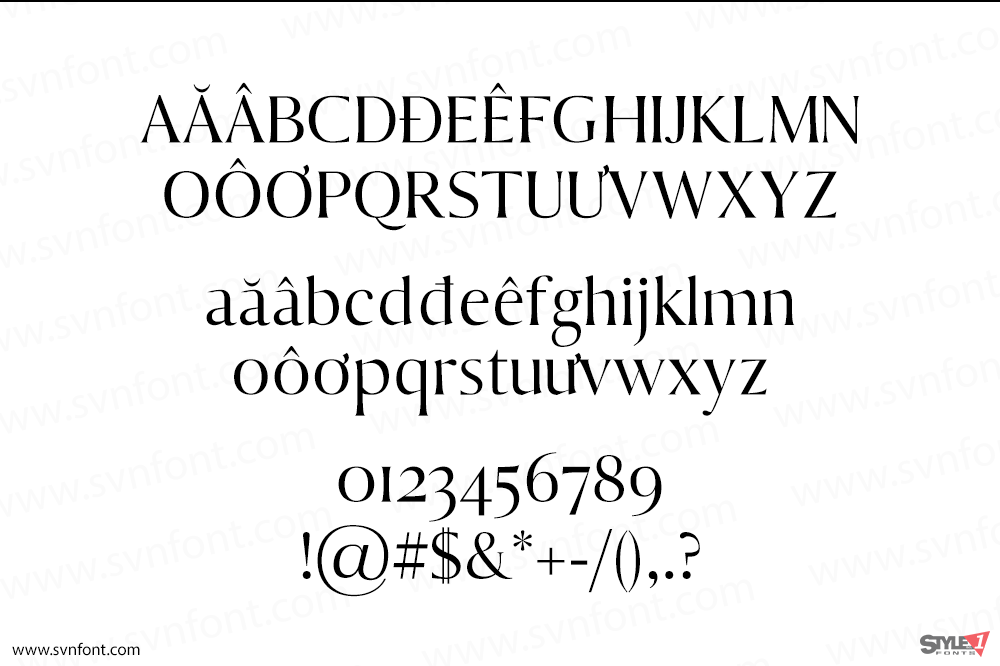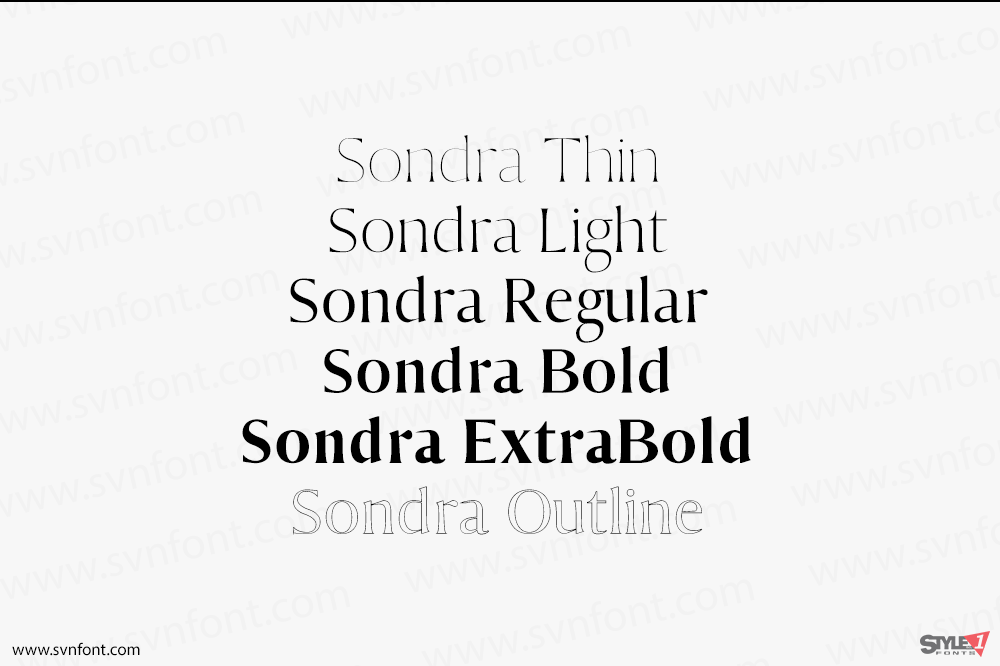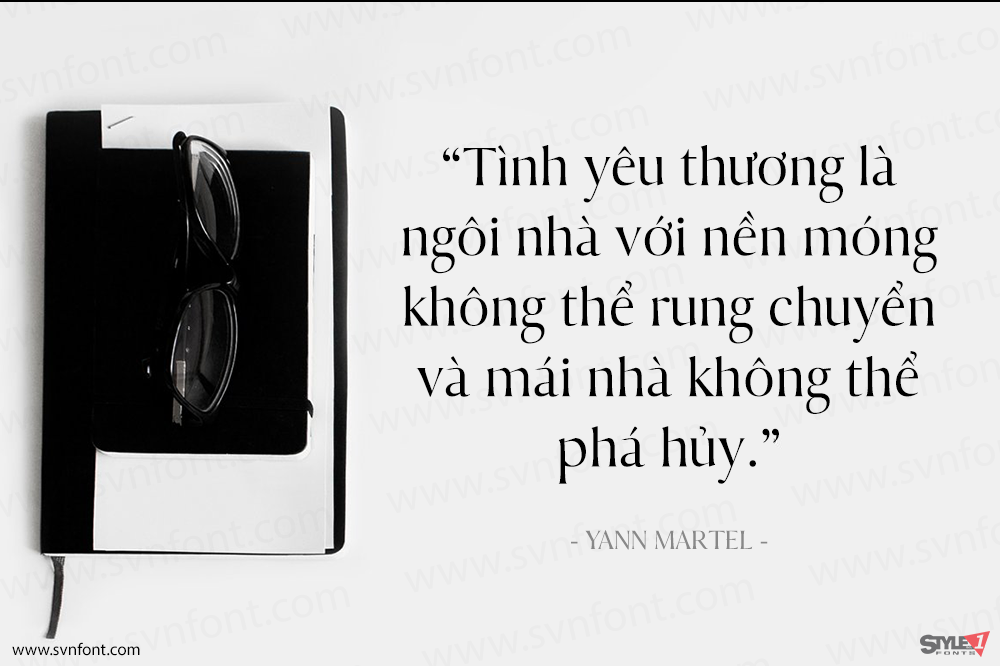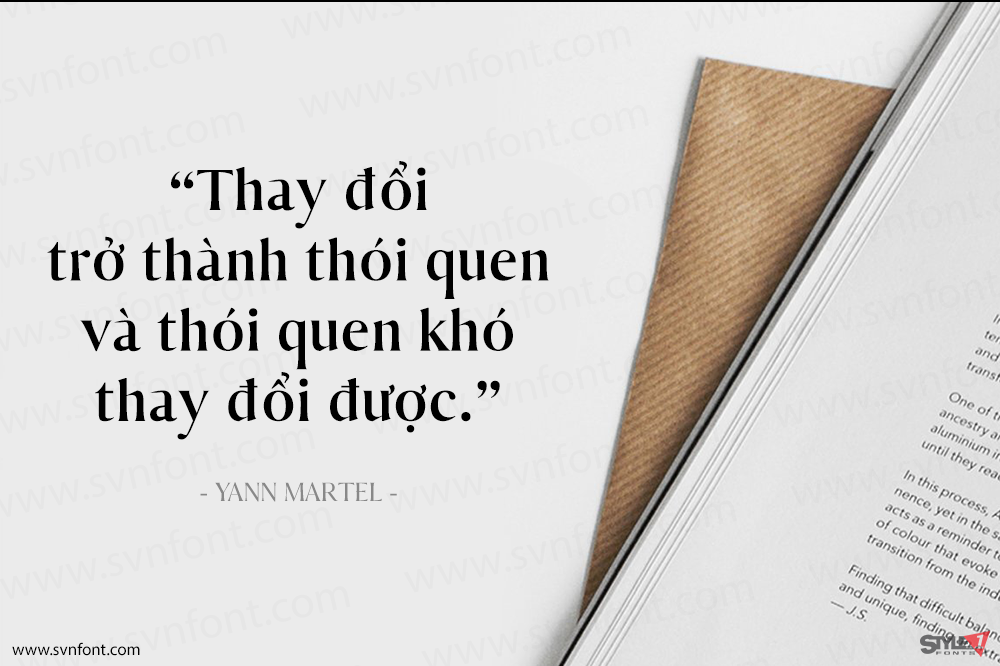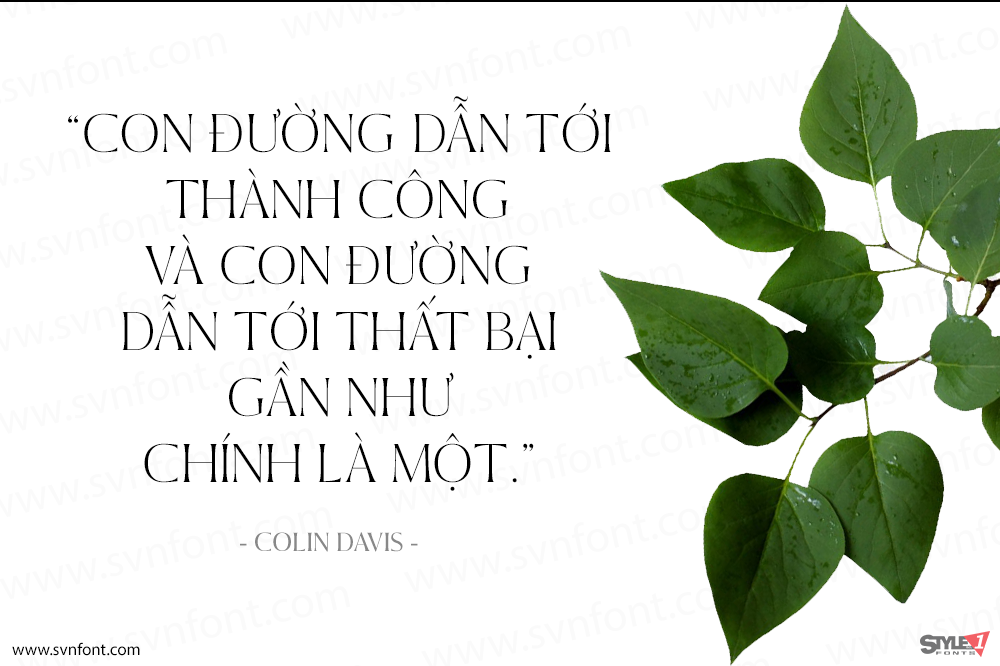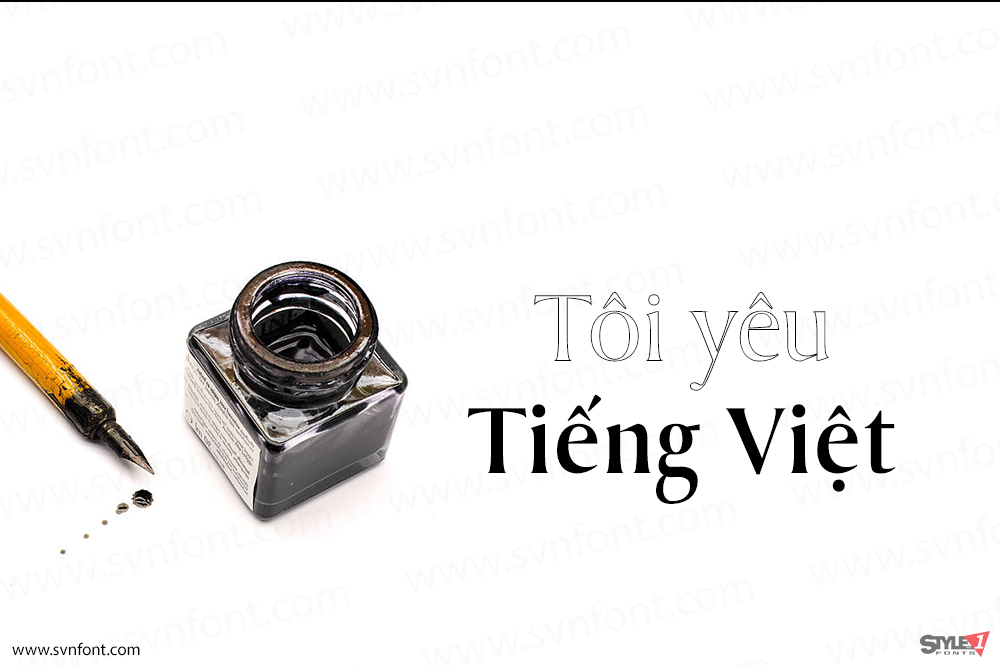
Sondra Serif Typeface là một họ font serif tối giản và đẹp mắt gồm 6 độ đậm, mang đến vẻ ngoài serif độc đáo và hiện đại. Hoàn hảo cho các logo & tiêu đề tuyệt đẹp, bố cục & nội dung, hoặc dù lớn hay nhỏ, font này trông rất đẹp khi viết hoa tất cả các chữ cái với khoảng cách rộng nếu bạn muốn thử một phong cách sang trọng, hoặc tự nó đã rất đẹp khi kết hợp chữ hoa và chữ thường cho một phong cách vượt thời gian.
Nhà thiết kế: Mohammad Ahsan
Nhà phát hành: Creativetacos